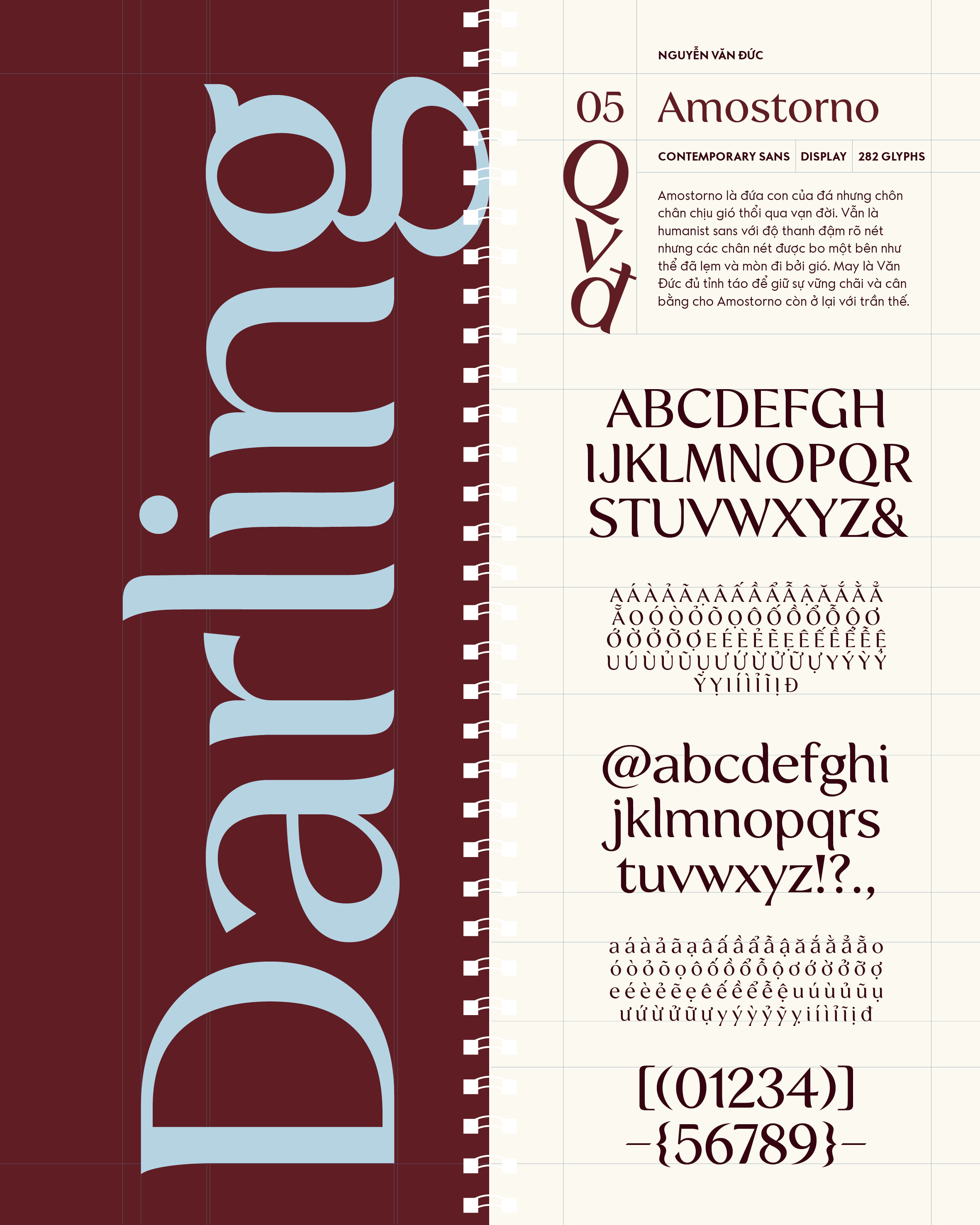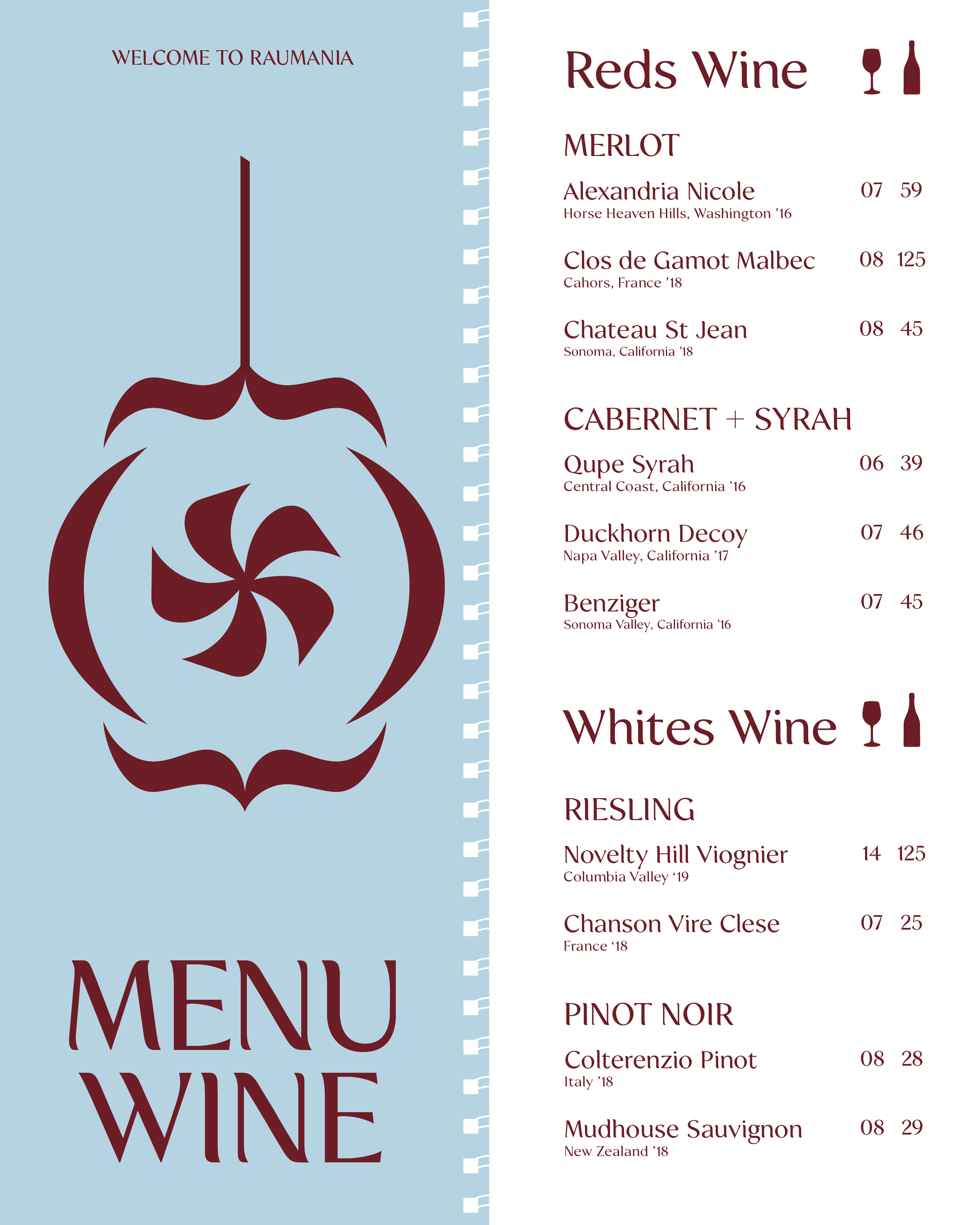
Amostorno
Về Amostorno: Amostorno là đứa con của đá nhưng chôn chân chịu gió thổi qua vạn đời. Vẫn là humanist sans với độ thanh đậm rõ nét nhưng các chân nét được bo một bên như thể đã lẹm và mòn đi bởi gió. May là Văn Đức đủ tỉnh táo để giữ sự vững chãi và cân bằng cho Amostorno còn ở lại với trần thế.
Contemporary Sans-serif
Display
Nguyễn Văn Đức
Amostorno
Saxophone
Amostorno
Mediterranean Originals
Amostorno
Chén rượu
Amostorno
Nắng sớm ăn cua
Amostorno
Mediterranean Originals, when approached more concretely, draws from a wide range of historical and material sources across the Mediterranean basin, including ancient Greek and Roman inscriptions, Renaissance lettering, and vernacular signage from coastal towns.
Amostorno
Letterforms in this tradition often show a balance between geometry and irregularity, classical proportions inherited from stone carving coexist with the spontaneity of hand-painted signs. The influence of climate is also significant: strong sunlight and weathering conditions have historically affected how colors, contrast, and stroke weight are perceived, leading to bolder forms, high legibility, and durable compositions. Materials such as stone, ceramic tiles, and painted wood contribute to a tactile visual language where typography is not just printed but embedded in physical space. Additionally, trade and cultural exchange across the Mediterranean have resulted in hybrid visual forms, where Latin, Greek, and sometimes Arabic influences intersect, making “Mediterranean Originals” less of a fixed style and more of a layered, evolving visual ecosystem rooted in everyday life and long-standing craft traditions.